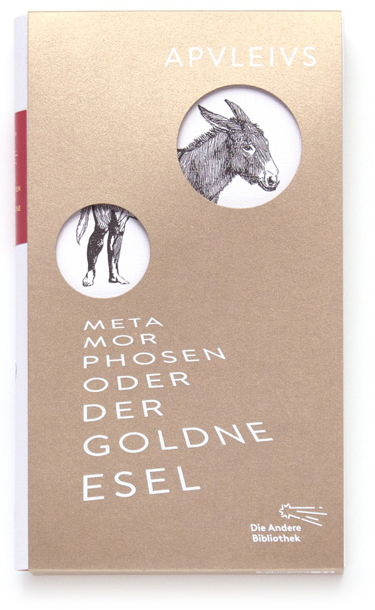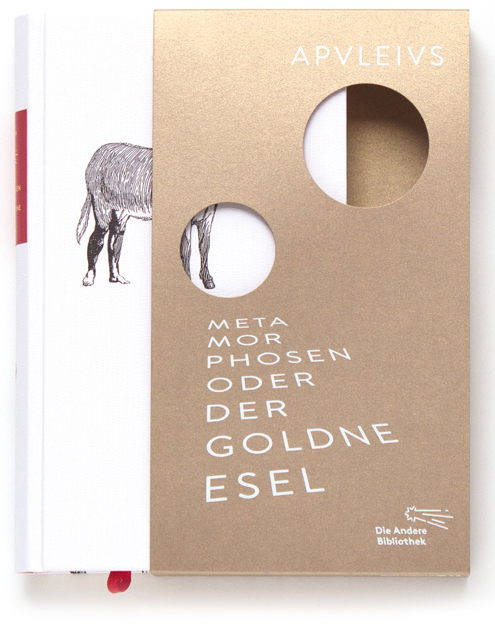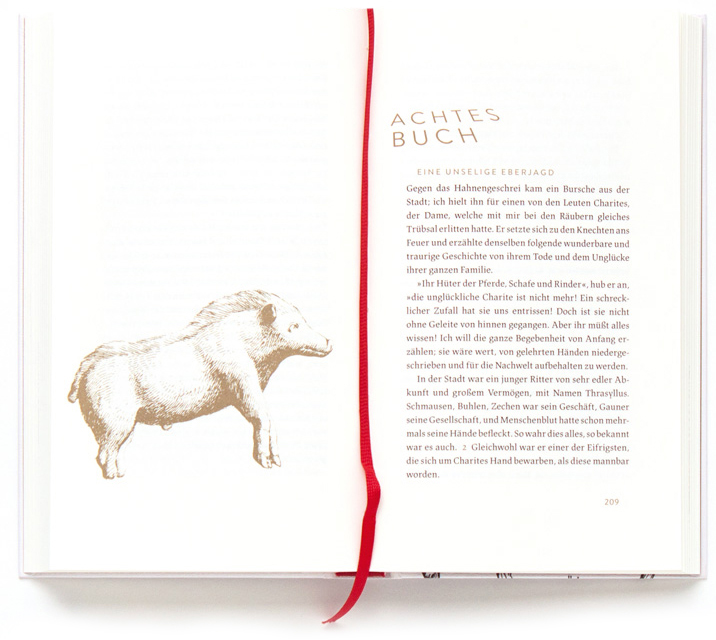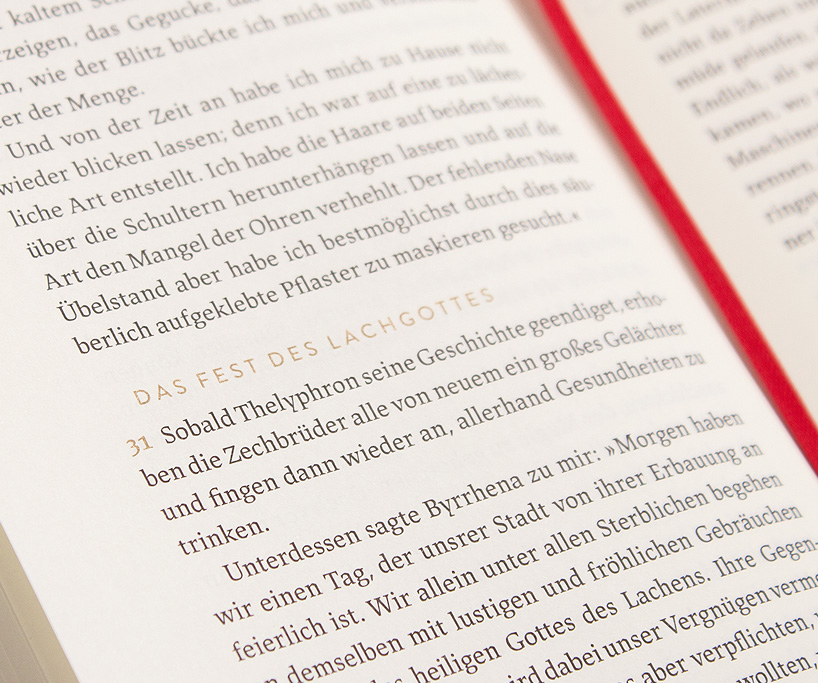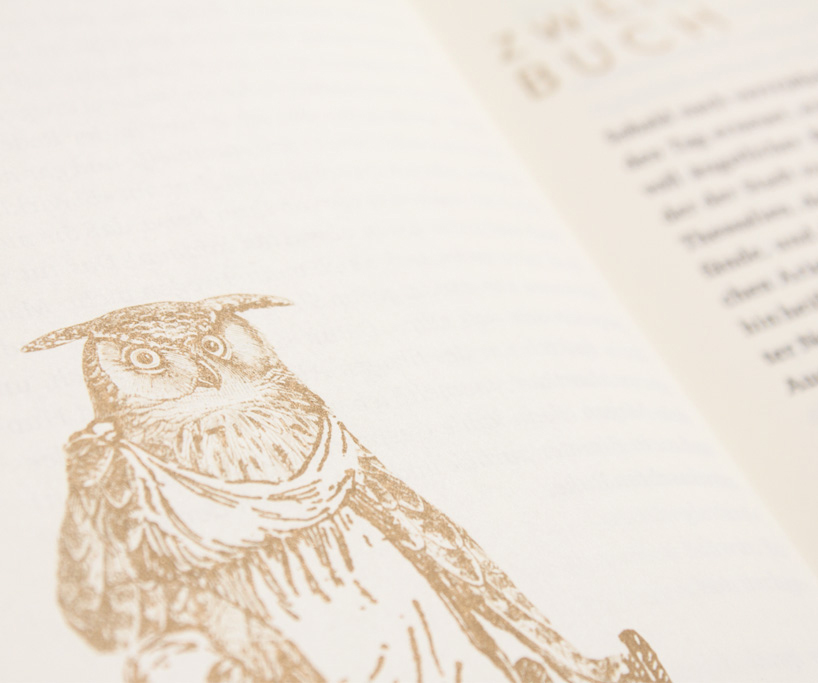
Apuleius
»Metamorphosen oder Der goldne Esel«
Über die Gestaltung
Apuleius’ »Metamorphosen« wurden in den fast 2000 Jahren ihrer Rezeption Geschwollenheit und Chaos attestiert, gleichzeitig wurden Hohelieder auf die kunstvoll verwobene Textstruktur und die formale Vielschichtigkeit des Romans gesungen. Ein auf vielen unterschiedlichen Wegen zu ergründender Text also, zu dem der Zugang ganz unterschiedlich aussehen konnte.
Entsprechend bunt waren auch die ersten Entwürfe, für die die unterschiedlichsten Elemente Verwendung fanden, nur nicht das Motiv »Esel« und die Farbe Gold – denn das wäre ja zu naheliegend gewesen. »Amor und Psyche« in diversen Varianten tauchten auf, als Gemälde, als historische Illustrationen des Romans im Original, verfremdet, gerastert, stilisiert. Das Ergebnis: Es war alles zu viel.
So schaffte es letztlich doch der Esel bzw. der sich in ihn verwandelnde Protagonist Lucius auf den Einband, und nur er. Auf einem hochweißen, strukturierten Papier, das einen optischen und haptischen Kontrast zur Schlaufe in Gold bildet, die nicht nur auf den Romantitel Bezug nimmt – sondern auch darauf, dass es etwas zu feiern gab: den 400. Band der »Anderen Bibliothek«. Das Gold leitet über das Vorsatz in den Innenteil, wo es die Auszeichnungsschriften belebt. Der Titel auf der Schlaufe, gesetzt in der »Brandon Grotesque«, nimmt das Weiß des Einbands auf und steht in seiner räumlichen Anordnung für die gesprochene Sprache: Der Überlieferung nach war Apuleius nicht nur Autor und Philosoph, sondern auch Rhetoriker.
Im Innenteil spielt die räumliche typografische Darstellung nur bei den Kapiteleingängen eine Rolle; ansonsten war das gestalterische Anliegen, die halb ironisch, halbe ernsthafte Berg- und Talfahrt des Protagonisten Leserin und Leser möglichst ruhig anzubieten.
Die Textschrift ist die »Lapture« von Tim Ahrens (nach Albert Kaprs »Leipziger Antiqua«) – nicht zuletzt wegen ihrer kleinen Brüche, als leiser Verweis auf die Ambivalenz des Textes. Die ruhigen Illustrationen begleiten nur die Kapiteleingänge.